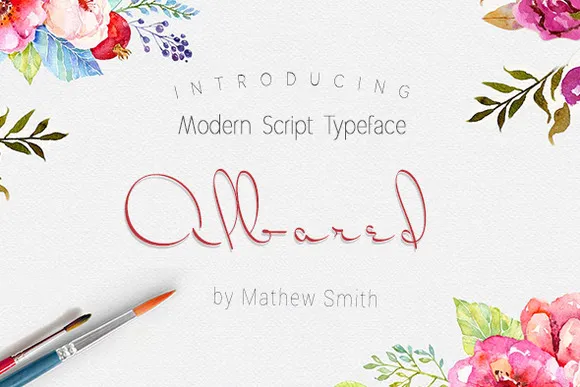
Albared Script Font – Download Grátis
Albared Script Font é uma delícia para aqueles que buscam personalidade em suas criações digitais. Inspirada na arte do traçado manual, esta elegante e natural fonte é perfeita para qualquer projeto que deseje um toque autêntico de design gráfico atraente e sofisticado. Com seu estilo de script, Albared não apenas adicionará um toque único ao texto, mas também fará sua mensagem soar ainda mais respeitável e impecavelmente bem projetada. Esta fonte é ideal para uma variedade de aplicativos que exigem um sabor autêntico do design gráfico. Perfeita para cabeçalhos, assinaturas, logomarcas, convites de casamento, camisetas personalizadas e anúncios em folhetos – Albared tem a capacidade de transformar qualquer peça em algo inovador e memorável. Seja você um designer gráfico profissional ou alguém que simplesmente deseja incorporar uma fonte única em seus projetos pessoais, Albared Script Font é o item perfeito para sua coleção.